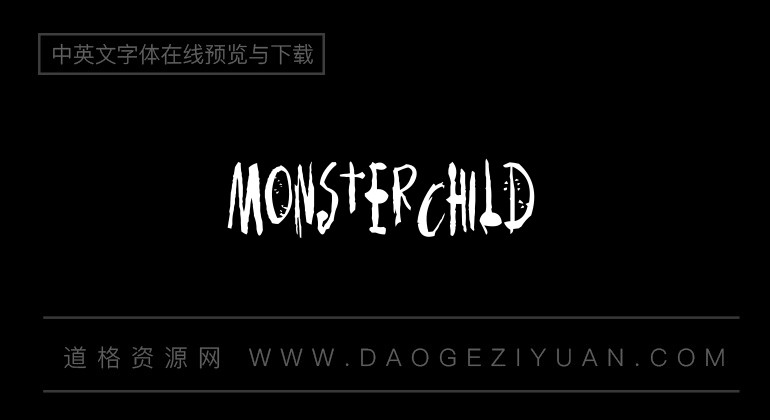
Monsterchild
Monsterchild是一种装饰性的手写风格字体,由字体设计师Jonathan S. Harris制作。这种字体的特点是其弯曲的线条和粗重的笔画,给人一种独特的印象。Monsterchild字体被设计为非常适合用于海报、书籍封面、音乐专辑封面、标志等设计领域中。该字体有四种不同的字重,并包括大写字母、小写字母、数字和标点符号。它的设计旨在吸引目光,并增加设计作品的视觉吸引力。
Monsterchild是一款非常不错的手写艺术字体,具有很好的视觉感,适合于文化类的宣传设计、商业类品牌的广告和产品包装设计以及个性化文字排版等较多场景。